Schriftbreite
»Schriftbreite« ist ein typografischer Terminus für die Breite eines gedruckten oder virtuellen Buchstabens oder Schriftzeichens einer Schrift bzw. eines Schriftschnitts (Schriftstils) innerhalb einer Schriftfamilie; horizontale Breite eines Buchstabens ohne Vor- und Nachbreite (siehe Dickte); Buchstabenbreite; Zeichenbreite.
Bei Textschriften bzw. Werksatzschriften mit Serifen entspricht die »Normalschriftbreite« (normal) bzw. die »Basisschriftbreite« traditionell in den Lesegrößen rund 4/5 der Majuskelhöhe (Grundlinie zur H-Linie) und bei Kleinbuchstaben – übertragen auf die Referenzbreite der Minuskel »n« – in etwa einem Halbgeviert (siehe Geviert).
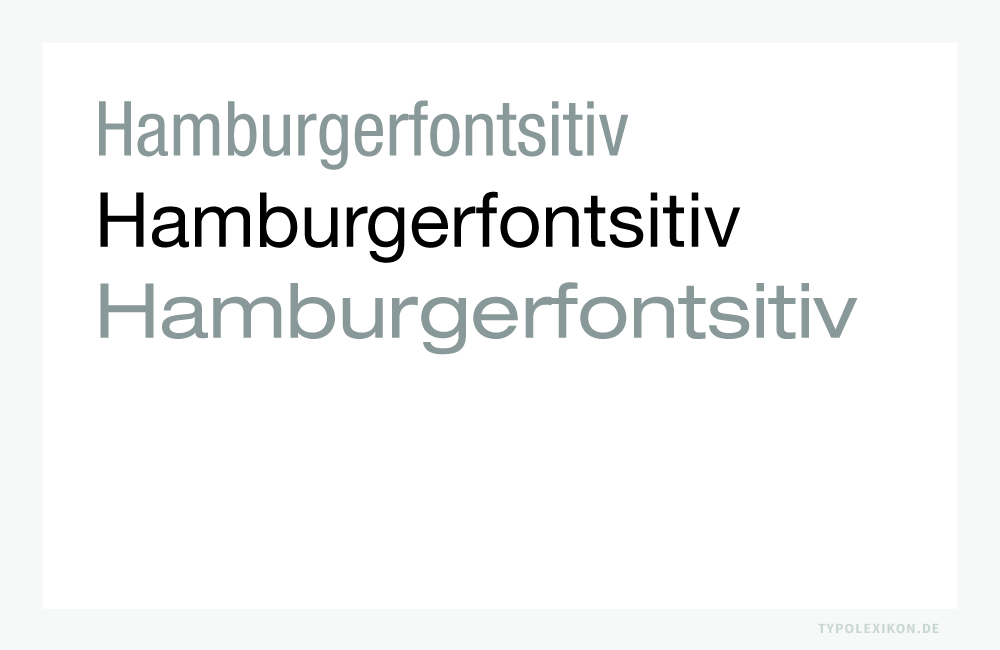
Ausgehend von der Normalschriftbreite (normal) sind bei Schriftfamilien und Schriftgarnituren folgende Schriftbreiten üblich:
- eng (condensed)
- schmal (smal)
- normal (regular)
- breit (extended)
- extrabreit (extra-wide)
In Verbindung mit unterschiedlichen Schriftlagen und Schriftstärken können sich daraus viele und teils exotisch klingende Kombinationen, z.B. »Kapitälchen schmalmager kursiv«, ergeben. Bei Expertensätzen sind die Schriftbreiten auch auf die unterschiedlichen Optischen Größen (Optical Sizes) einer Schriftfamilie abgestimmt.
In traditioneller Anlehnung an den gewerbespezifischen Sprachschatz dspr. Schriftsetzer, Schriftgießer und Drucker aus der Periode des materiellen Schriftsatzes mit physischen Drucktypen aus Metall (z.B. aus einer Blei-Zinn-Antimon-Kupfer-Legierung) wird die »Schriftbreite« bzw. »Buchstabenbreite« heute irrtümlich auch als »Dickte« bezeichnet. Dies ist jedoch inkorrekt, da sich die Dickte – also die Schriftkegelbreite – auf die Zeichenbreite plus Vor- und Nachbreite bezieht, also sowohl die druckenden als auch die nichtdruckenden Flächen umfaßt.